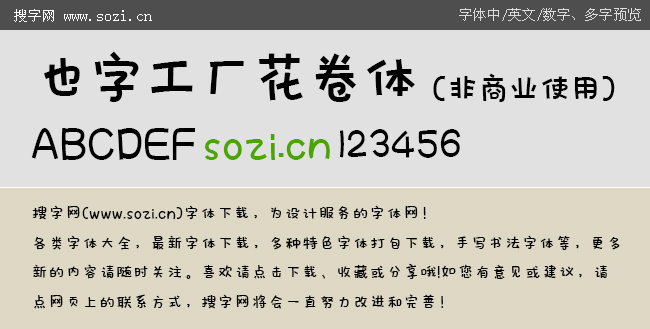
也字工廠花卷體
搜字網(wǎng)給大家提供一款也字工廠花卷體(非商業(yè)使用)中文字體下載,也字工廠花卷體是一款卡通字體,字體書寫可愛有趣,充滿童真。具有很好的視覺效果。適合應(yīng)用于藝術(shù)設(shè)計(jì)、平面宣傳設(shè)計(jì)、網(wǎng)頁(yè)設(shè)計(jì)、海報(bào)設(shè)計(jì)等應(yīng)用(此字體為個(gè)人非商用版,商用可以聯(lián)系:官方網(wǎng)址:https://yefont.com/home,聯(lián)系方式:13798980448)。